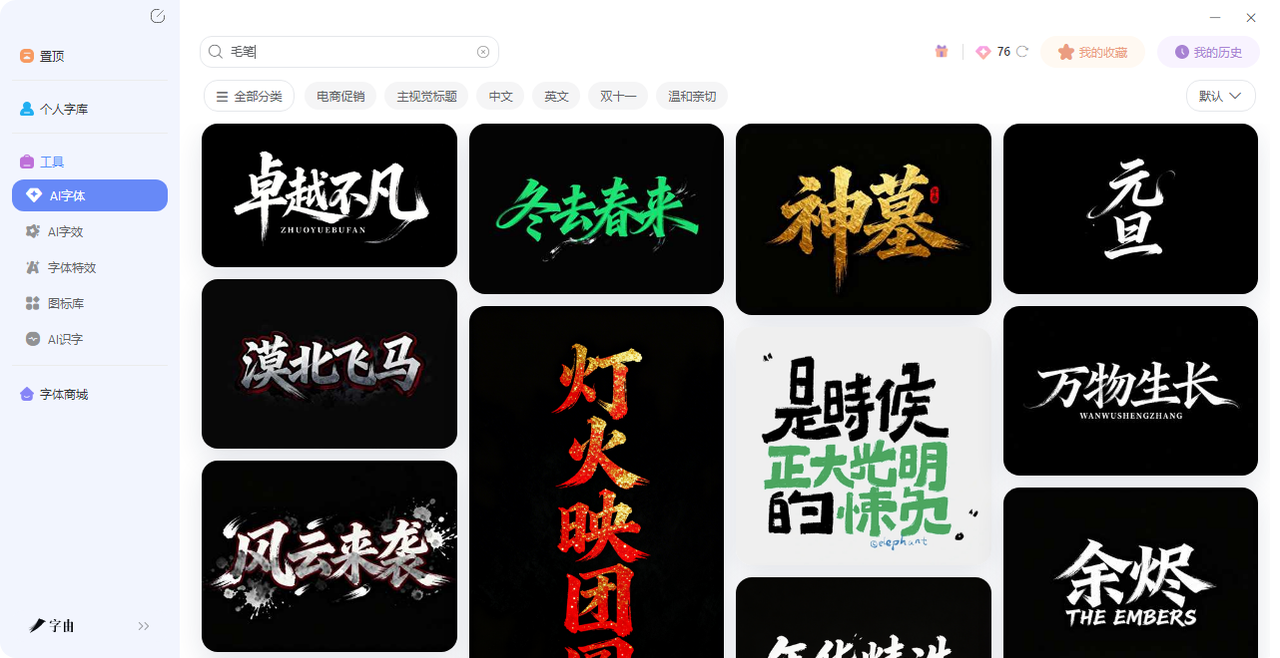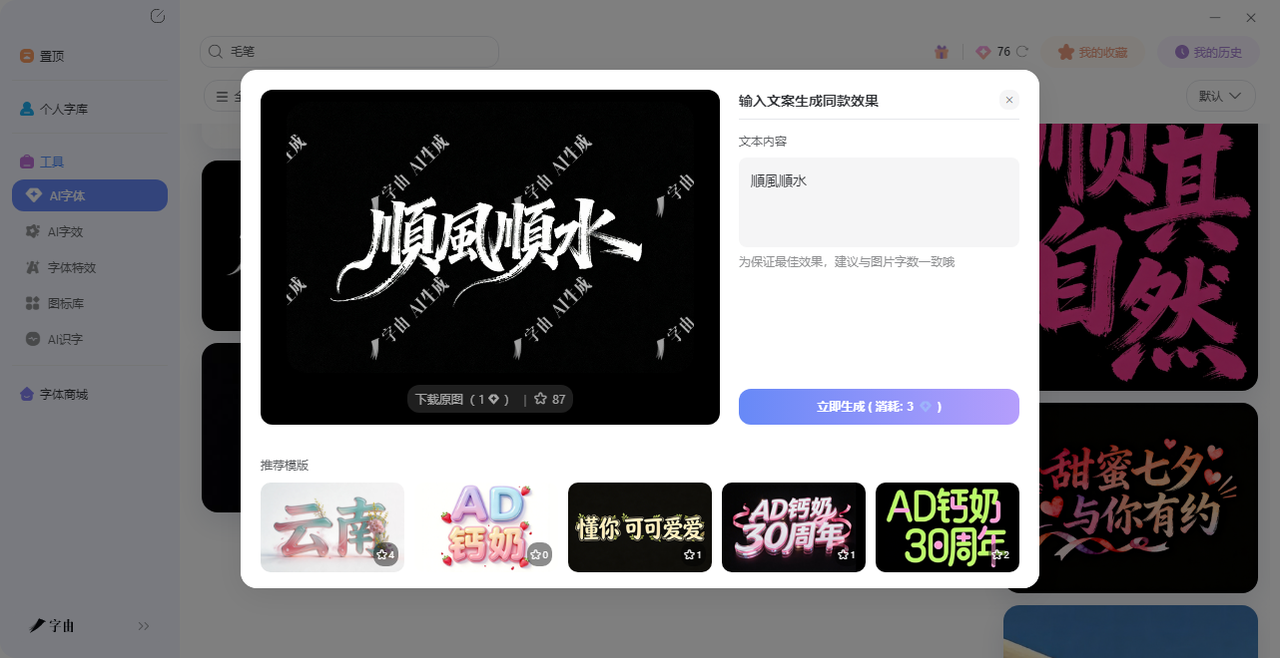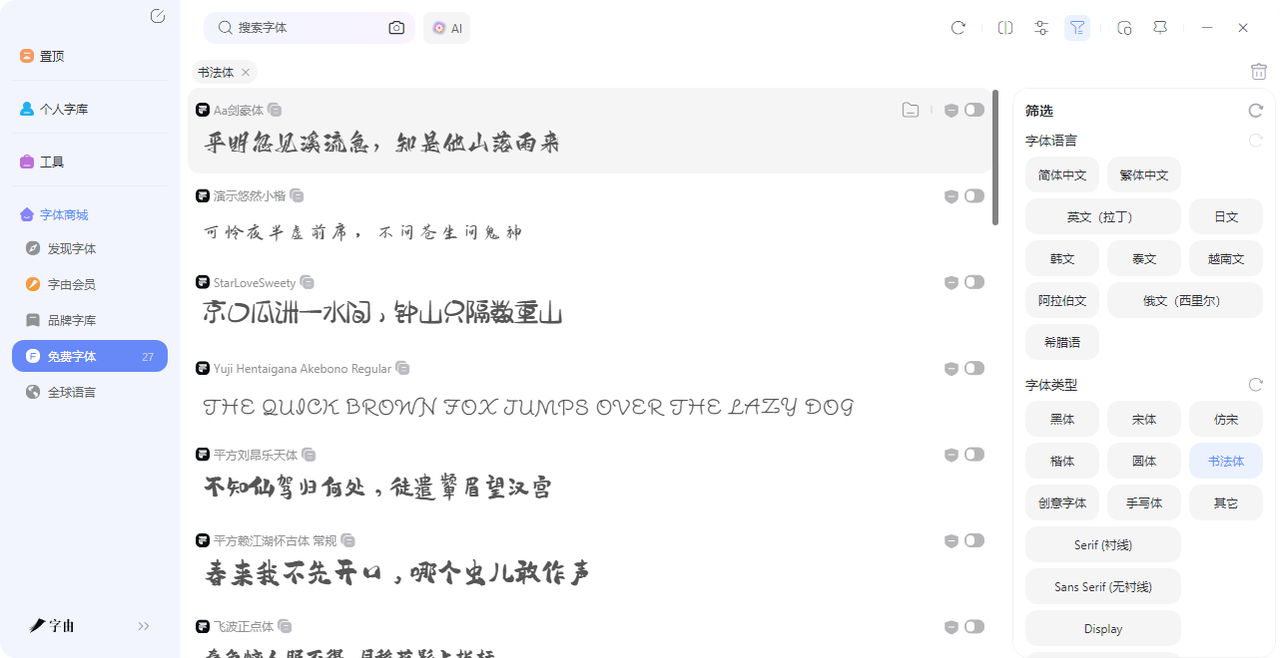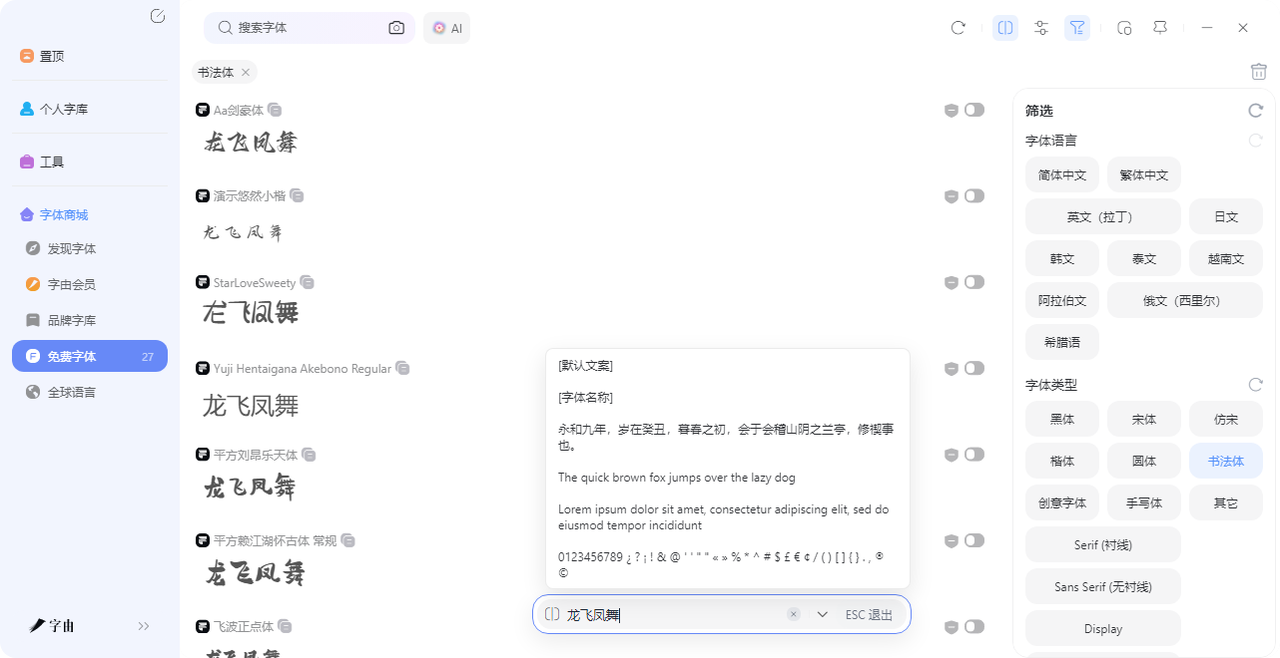
毛笔字体转换器在线生成:一个工具就可以搞定
还在辛辛苦苦手搓字体?还在从网上费时费力地找毛笔字?其实这些问题只需要一个工具就可以解决,完全不用那么复杂,现在有种工具叫毛笔字体转换器——你输入文字,它直接帮你转换成毛笔书法风格的效果。有的是生成图片,有的是直接给你可用的字体文件。今天我就向大家介绍一款工具:字由。它从三个不同角度帮你实现“毛笔字体转换”,每个角度适合不同场景。看完你就知道,选对方法,做书法风格的设计可以很简单。
1、字由相关介绍
此外,字由还提供了AI字体、AI字效、AI识字、AI擦除、AI配字等一系列智能工具。其中AI字体功能允许用户输入文字并选择风格模板(如书法风、电商促销、主视觉标题等),系统自动生成艺术字图片,可直接下载用于海报、封面等设计场景。
总之,字由不仅仅是一个字体平台,它是将于字体相关的一切事情集合在了一起,从字体发现、筛选、预览、版权确认,到一键应用到设计软件,再到AI辅助生成艺术字的完整流程。是一个功能性和实用性兼具的优秀字体网站。
下面我将会分三个方向来介绍如何用字由的毛笔字体转换器。
2、方向一:AI字体功能
如果你只是偶尔需要一句书法标题,比如“天道酬勤”“海纳百川”,不想装字体也不想调效果,那字由的 AI 字体 功能最合适。打开字由客户端,左侧导航栏找到“工具” → “AI 字体”。进去之后,你会看到各种风格模板。在风格筛选中选择“书法风”或者“毛笔字”相关分类,会出现一批专门做毛笔效果的模板。
这些模板不是字体文件,而是预设好的艺术字样式。你选中一个模板,比如“行书飞白”“粗笔狂草”“水墨晕染”,然后把默认文字改成你自己的内容,比如“厚德载物”。点击生成,几秒钟后,AI 就把你输入的文字渲染成一张毛笔书法风格的图片。
生成的图片可以下载 PNG,背景通常是透明的,方便直接拖进 PS、PPT 或者海报里。相比网上那些模糊的在线生成器,字由 AI 出的图分辨率高,没有水印,笔触细节保留得很好。
3、方向二:一键激活毛笔字体
如果你经常做设计,需要在 PS 或 Sketch 里反复使用毛笔字体,并且希望文字是可编辑的(方便改内容、调大小),那用字由的“字体库 + 一键激活”方式更合适。字由的字体库里收录了不少免费商用的毛笔书法字体,足够你使用。
找到喜欢的毛笔字体后,点击字体卡片上的“激活”按钮。然后打开 PS 或者 Sketch,在文字工具的字体列表里,就能直接找到刚才激活的那款字体。选中文字图层,切换到这个字体,你打的字瞬间变成毛笔书法效果。
4、方向三:字体详情页直接输入可查看预览效果
有时候你只是好奇某款毛笔字体在自己的文字上长什么样,不想激活,也不想下载。那字由的“详情页预览”功能就派上用场了。
在字由客户端里,点击任意一款字体卡片,进入详情页。详情页的上方有一个输入框,默认显示的是“字由”或者字体的示例文字。你把这个删掉,输入你自己的文字,比如“龙飞凤舞”。页面会实时把输入的文字替换成当前字体的样式。
这个预览是即时的,你改一个字,效果马上变。你可以反复输入不同文案,看看这款毛笔字体在不同字数和不同内容下的表现。比如有的毛笔字体写“一”很好看,但写“龍”字可能会显得拥挤;有的适合写两个字,写多了就不协调。不激活就能测试,省去了反复安装卸载的麻烦。
5、其他实用的小功能
那么从以上的内容看来,毛笔字体转换器听起来像是一个专门的在线小工具,但其实字由一个平台就可以办到从三个角度都能帮你搞定这件事情,三个方法互不冲突,你可以根据实际需求切换。字由目前有很多款书法风格的免费商用字体,加上 AI 生成功能,基本覆盖了从临时出图到专业设计的全部场景。去 hellofont.cn 下载个字由客户端,打开“AI 字体”选个毛笔模板试试,或者搜一下“行书”“草书”看看字体库。转换毛笔字,其实比你想的简单得多。